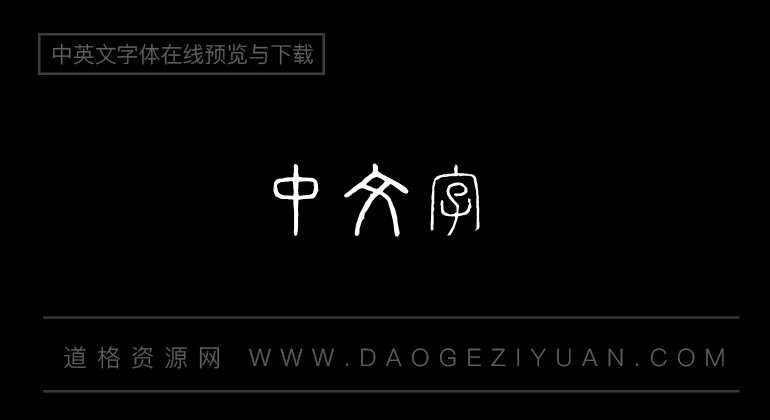
全字库说文解字(简称全字库)是汉字字体的一种,它是由中华人民共和国文化部于1998年颁布的《中华人民共和国文化部关于印制国家统一汉字字体全字库说文解字的决定》制定的。全字库字体是由中华人民共和国文化部批准的,它是汉字字体的一种,其特点是字形统一、笔画细腻、笔画完整、字体美观、字体大小可调。全字库字体是用于汉字输入和显示的,它可以保证汉字的统一性,从而使汉字在各种文化环境中保持其本质特征。文件名:QuanZiKuShuoWenJieZiZiTi-2.ttf
全字库说文解字是一款非常不错的手写艺术字体,具有很好的视觉感,适合于文化类的宣传设计、商业类品牌的广告和产品包装设计以及个性化文字排版等较多场景。